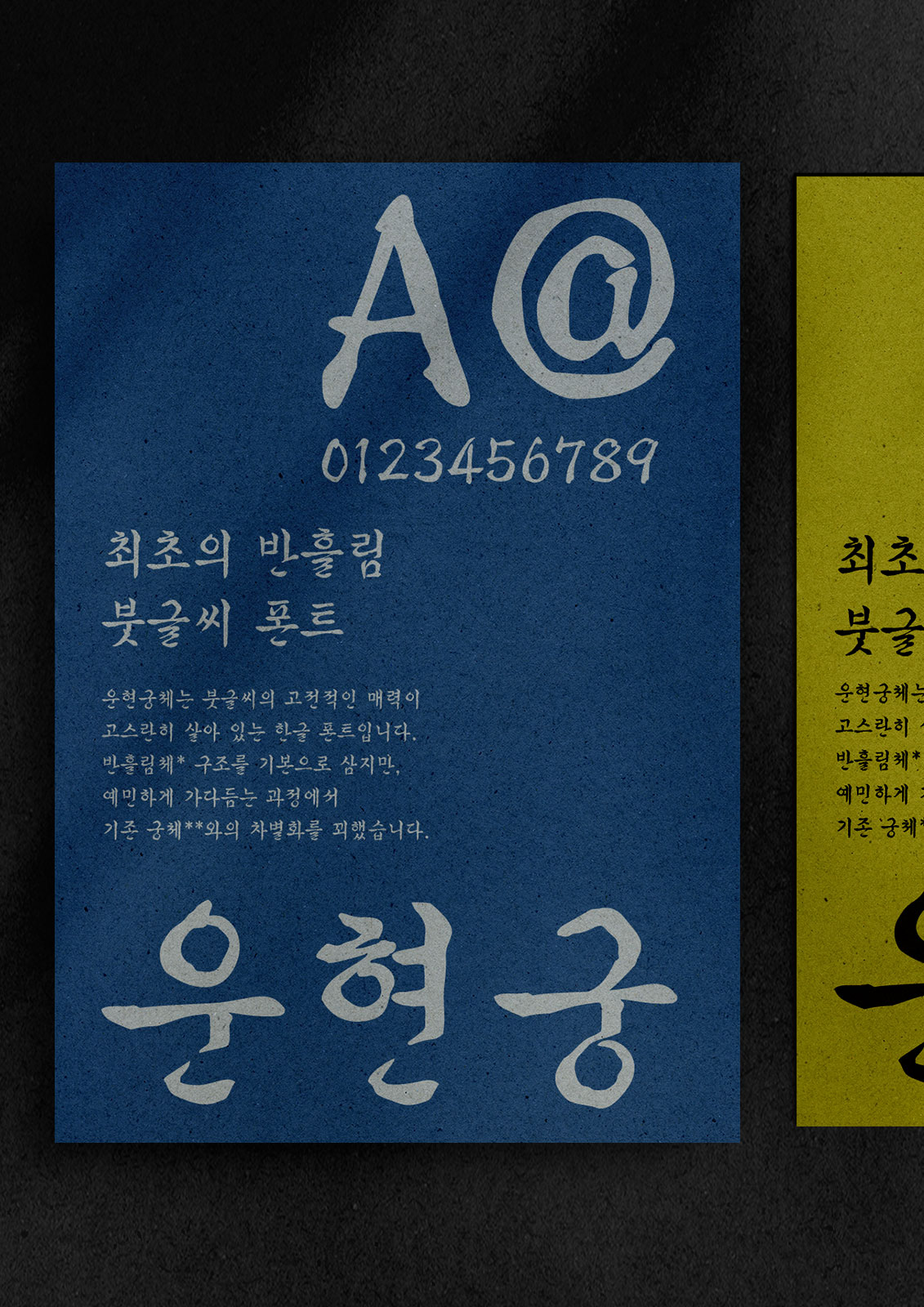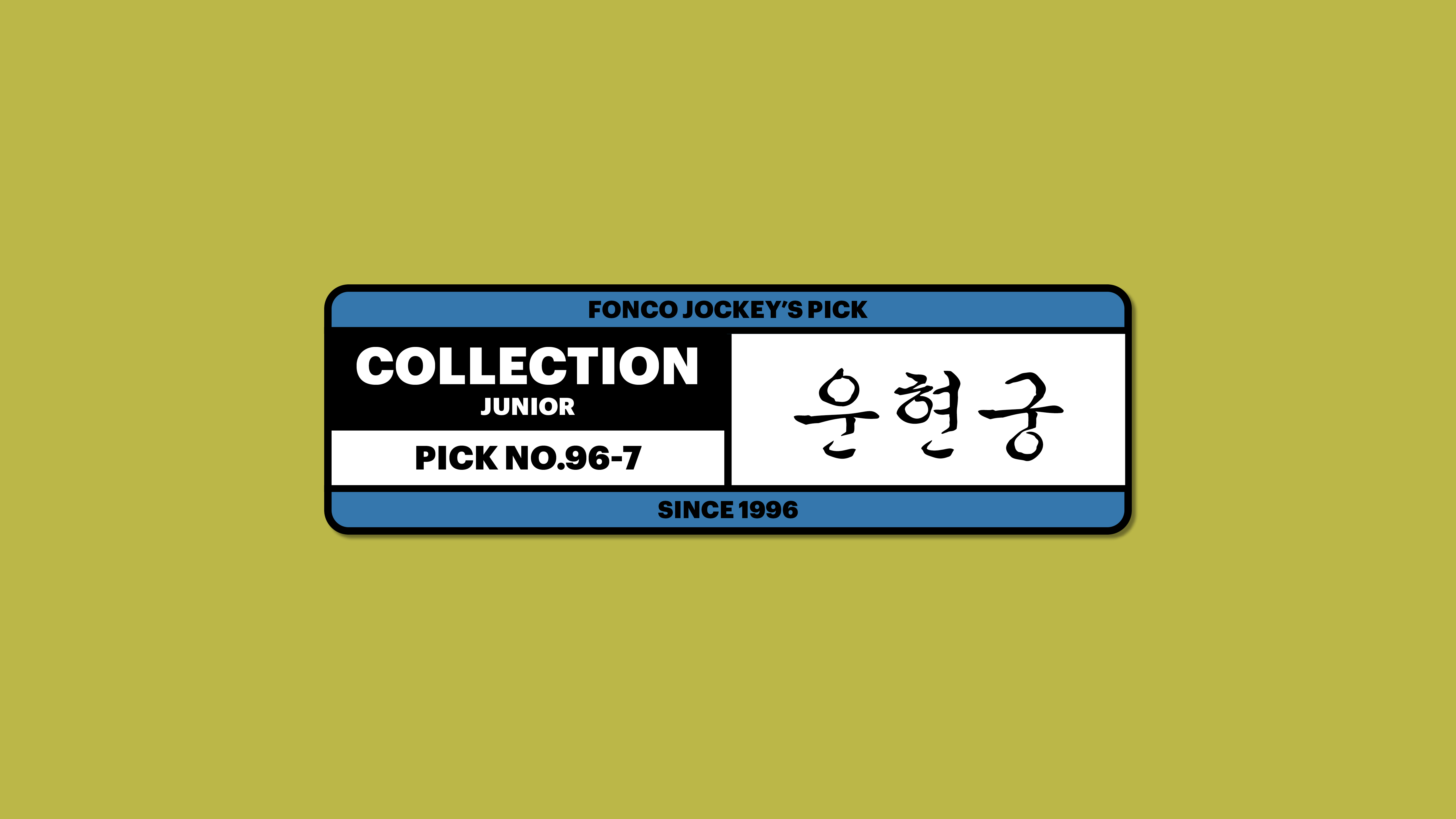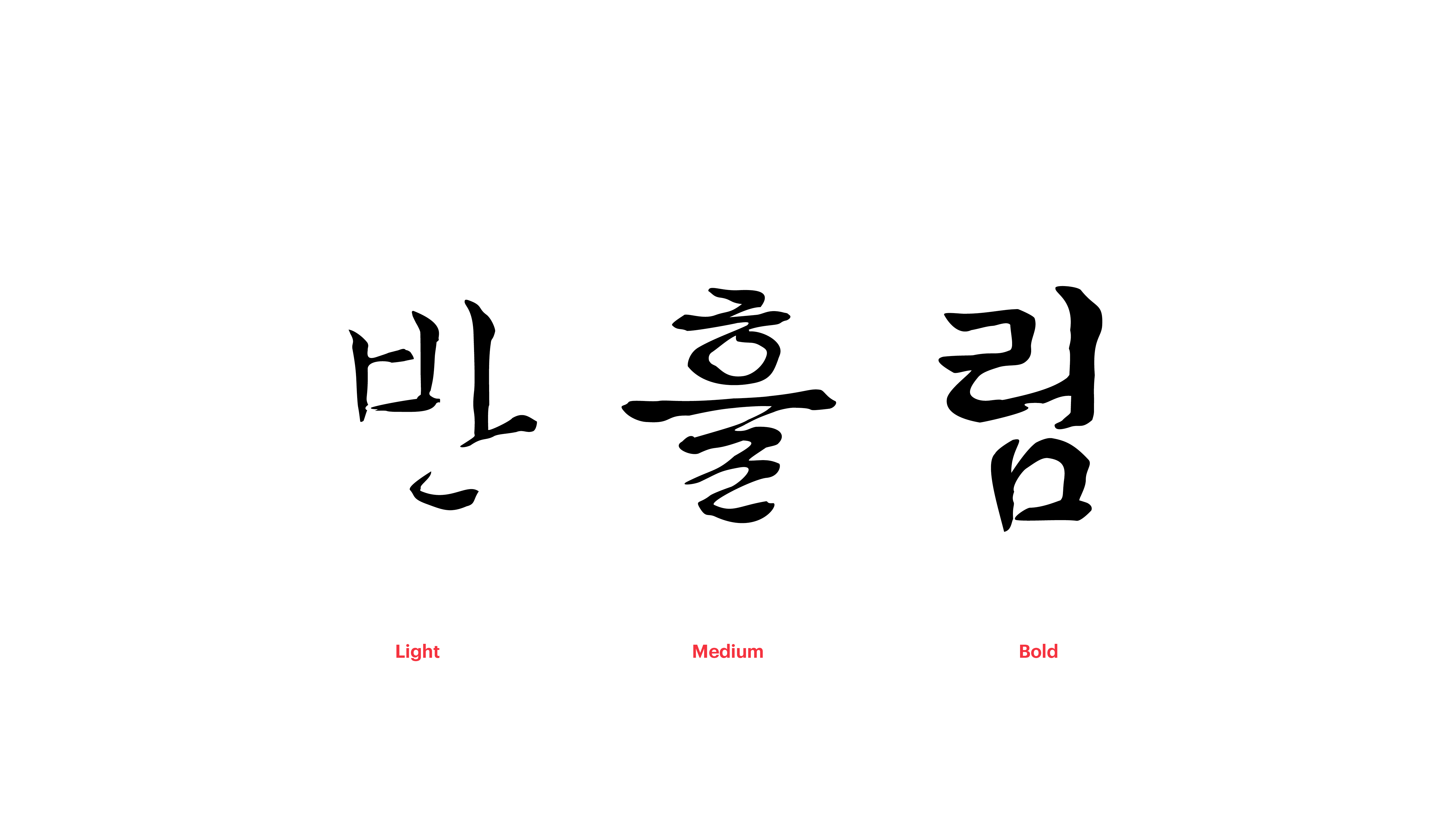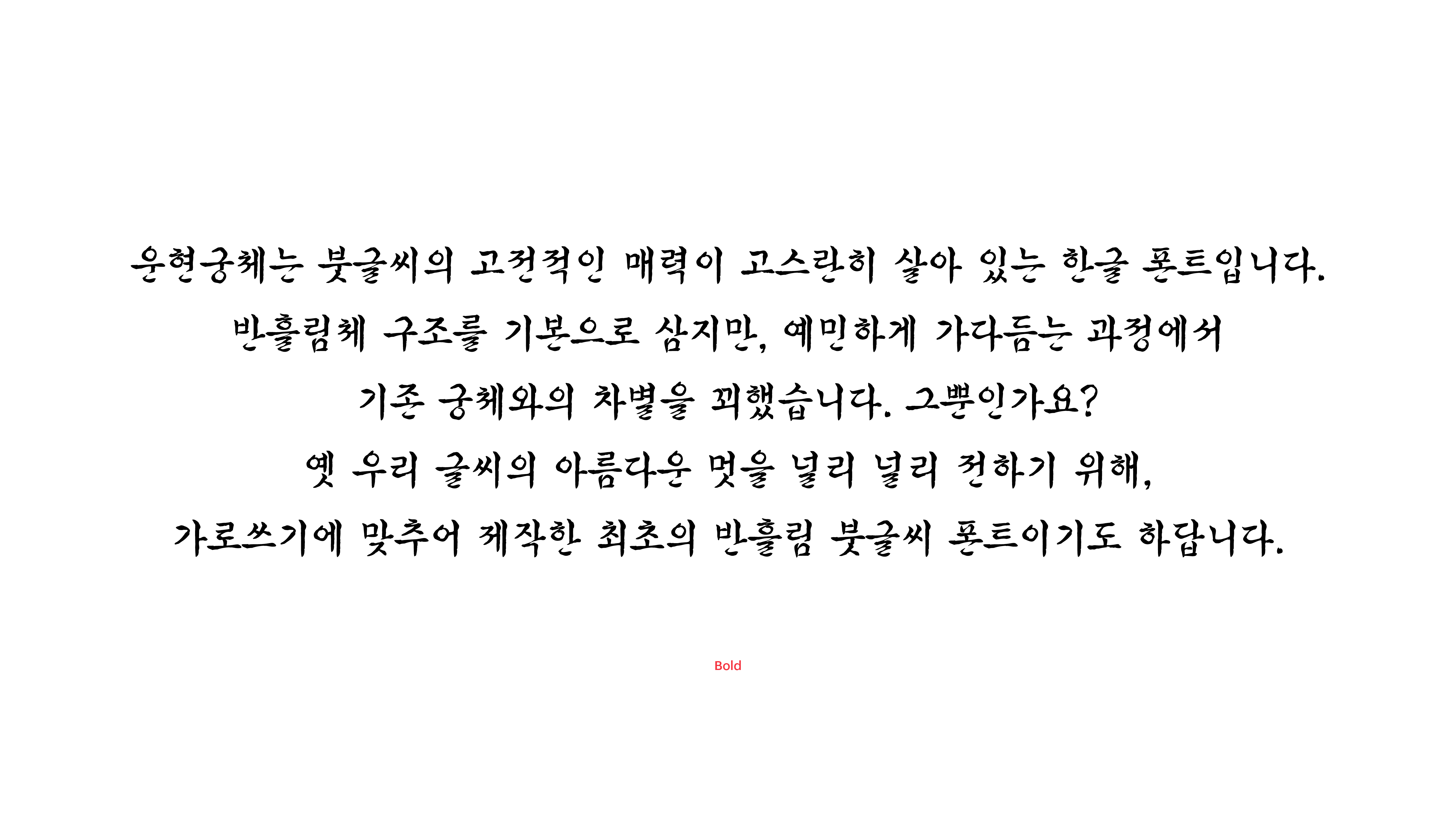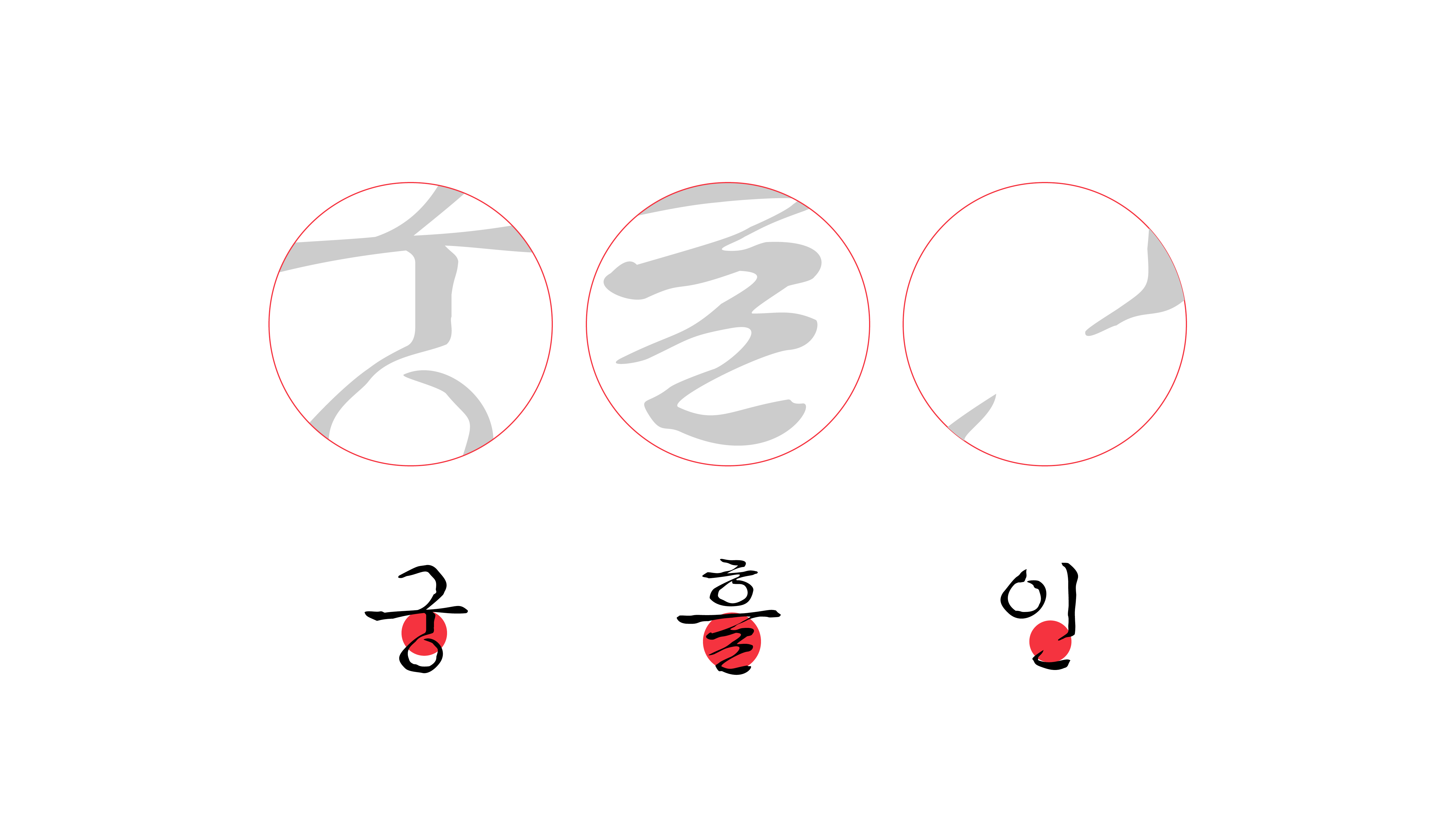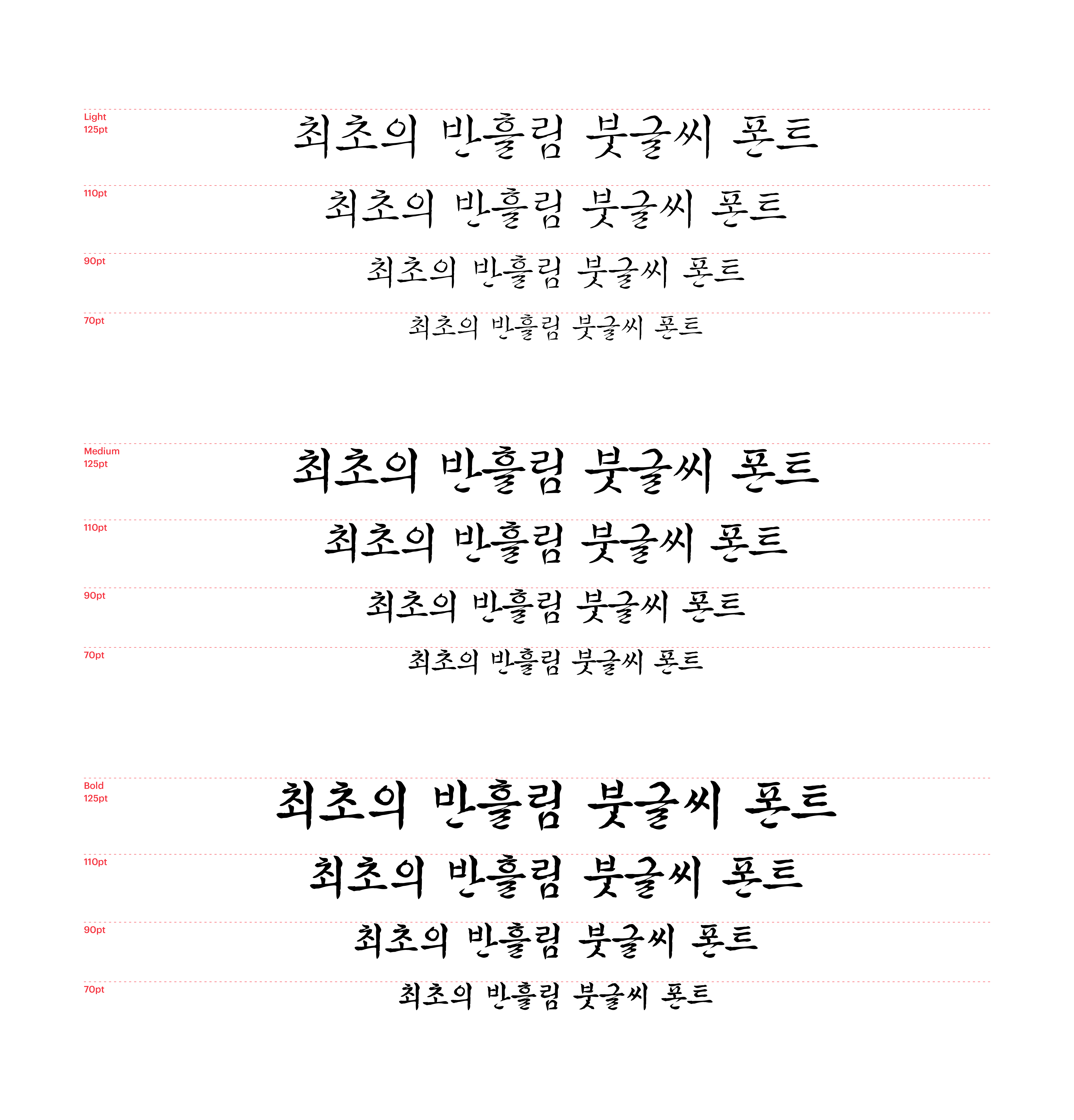
운현궁체는 붓글씨의 고전적인 매력이 고스란히 살아 있는 한글 폰트입니다. 반흘림체* 구조를 기본으로 삼지만, 예민하게 가다듬는 과정에서 기존 궁체**와의 차별화를 꾀했습니다. 그뿐인가요? 옛 우리 글씨의 아름다운 멋을 널리 널리 전하기 위해, 가로쓰기에 맞추어 제작한 최초의 반흘림 붓글씨 폰트이기도 해요. 하지만 이런 사실을 전혀 모르고 쓰더라도 그저 은은하고 아름답기만 하지요. *반흘림체 : 흘림과 정자의 중간이 될 만한 정도로 흘려 쓰는 글씨체. **궁체 : 조선 중기 이후, 한글 실용화의 단계에서 붓으로 쓰며 상용화된 정자체와 흘림체. 주로 궁중에서 형성되었다고 하여 궁중 서체 또는 궁체라고 부른다. 궁서체를 떠올리면 이해하기 쉽다.
Yoon 운현궁